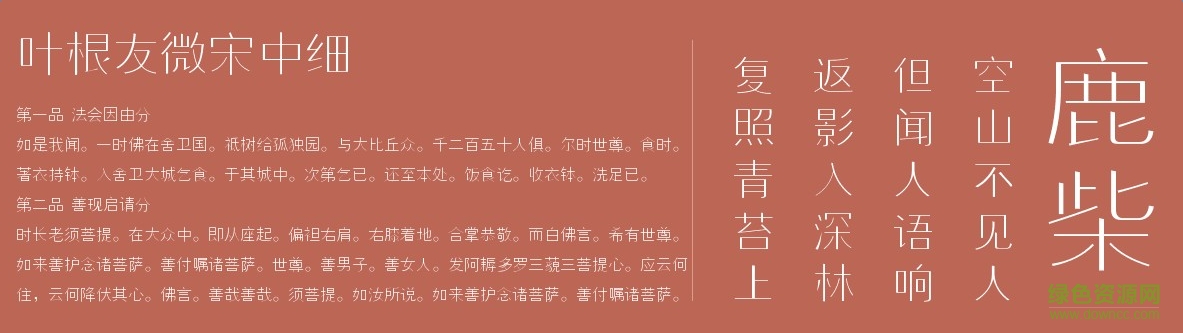
葉根友微宋中細(xì)字體是一款由知名書(shū)法家葉根友創(chuàng)造的字體,比劃圓潤(rùn),適用于廣告、藝術(shù)設(shè)計(jì),海報(bào)設(shè)計(jì)等方面,有需要的朋友們不要錯(cuò)過(guò)了。歡迎大家來(lái)綠色資源網(wǎng)踴躍下載哦!
葉根友微宋中細(xì),是一款個(gè)性十足的字體,菱角分明,動(dòng)感時(shí)尚,筆畫(huà)錯(cuò)落有致,是標(biāo)題字體和個(gè)性載體上非常貼切的選擇。
細(xì)宋體,用途廣泛,比較正式,適合場(chǎng)合很多,各位字體收藏者可以來(lái)看看。